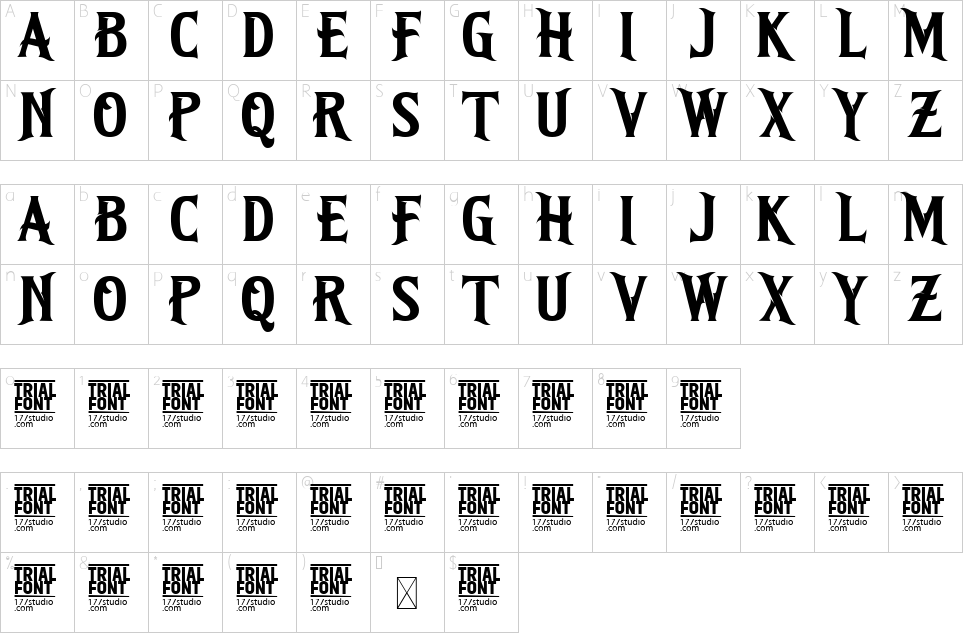
Descubra uma nova forma de expressar-se com a fonte “Different Discovery”. Inspirada no conceito de descoberta e inovação, esta fonte não apenas oferece um novo olhar para seu design, mas também reflete o espírito curioso do nosso tempo. Desenvolvida pela 177studio.com, ela traz uma paleta única de caracteres que vai além da versatilidade tradicional das fuentes. “Different Discovery” foi projetada para Windows e Mac, permitindo que você a personalize suas aplicações digitais de diversas maneiras. Com seu design moderno e fácil de ler, é ideal para criar textos atemporais ou estilos futuristas em sua próxima peça visual. Seja você um designer gráfico experimentando novas formas de expressão, ou um profissional de web buscando novos efeitos de texto, “Different Discovery” traz alegria à sua paleta de ferramentas. Agora é o momento de mergulhar nessa descoberta única com nossa fonte gratuita. Descubra seu potencial e deixe sua marca ser percebida em diferentes ambientes digitais.